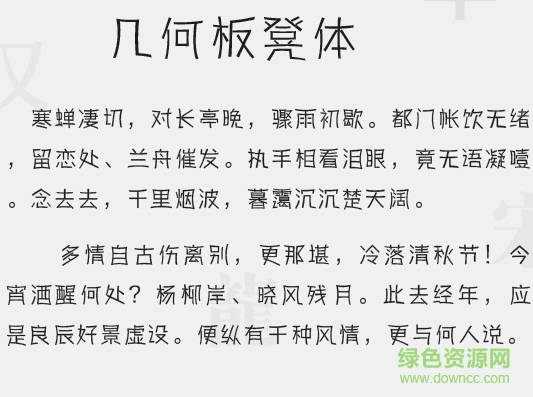
幾何板凳體字體
幾何板凳體是一款四方形的藝術(shù)字體,是幾何字體系列的全新字體模板,造型方正如果尺子測量過,給人一種清新婉約的藝術(shù)美感,喜歡的朋友千萬不要錯過,來綠色資源網(wǎng)收藏吧!
幾何板凳體字體介紹
幾何板凳體大方簡約,適合幾何內(nèi)容的排版設(shè)計,給人端正明朗的視覺好感,可廣泛運用于海報設(shè)計、文字印刷、編輯排版等行業(yè)。
幾何板凳體
幾何字體特色
用幾何圖形、線條創(chuàng)作出來的字體外形優(yōu)雅、大氣、整潔以及設(shè)計精巧,可用作正文或大標(biāo)題上使用,特別是一些喜歡簡約干凈的設(shè)計風(fēng)格,使用這些幾何字體就非常適合了!